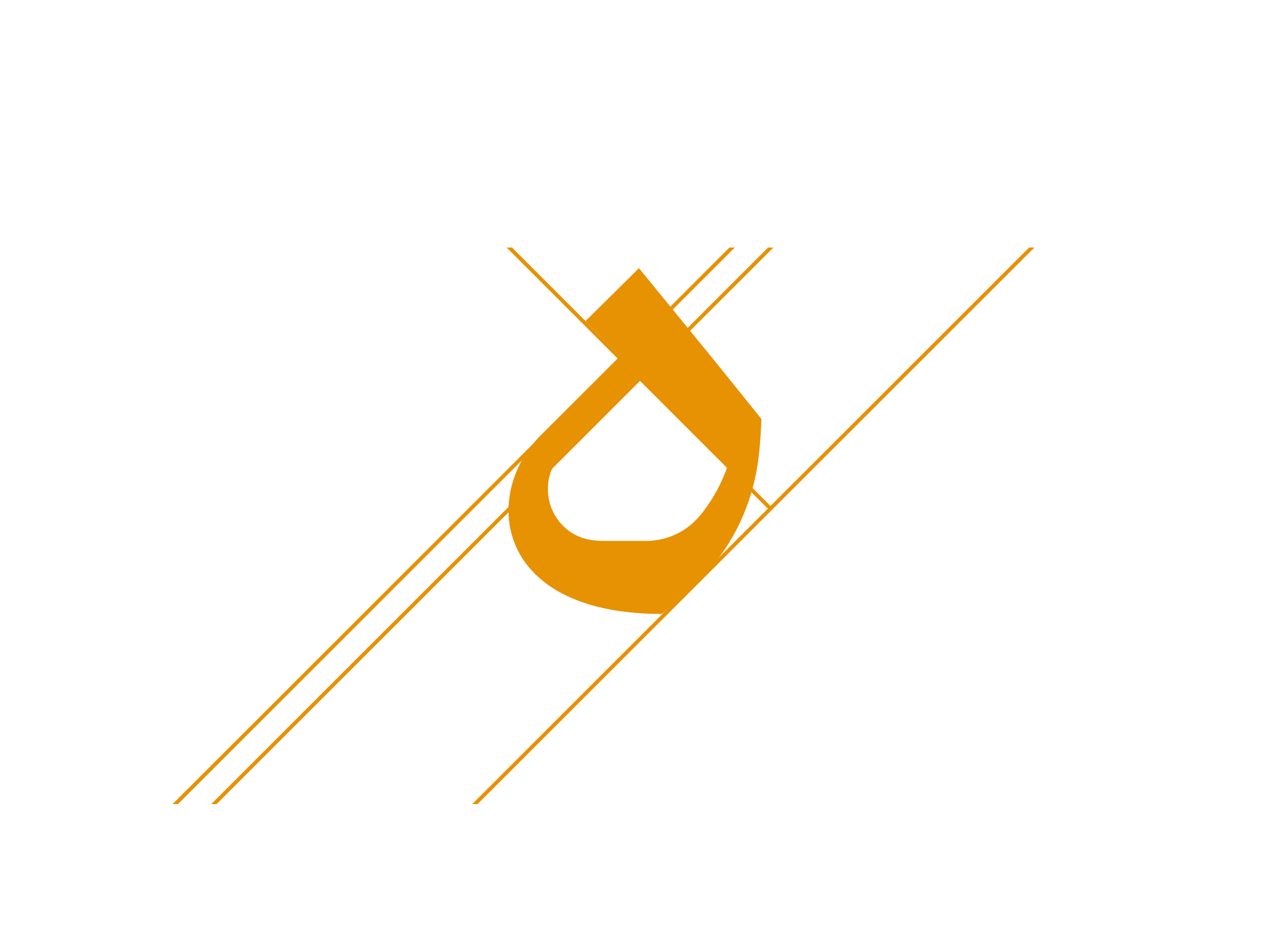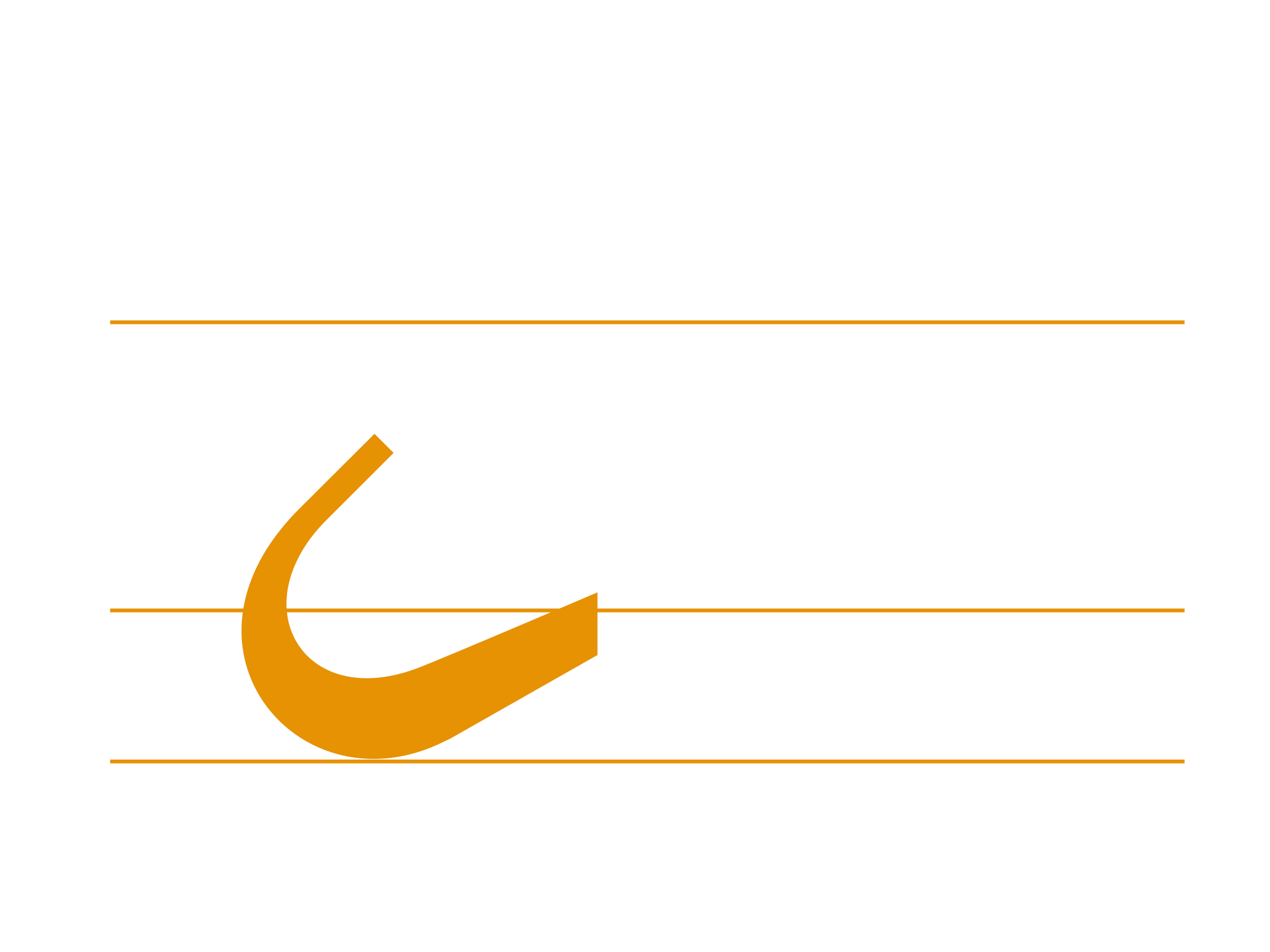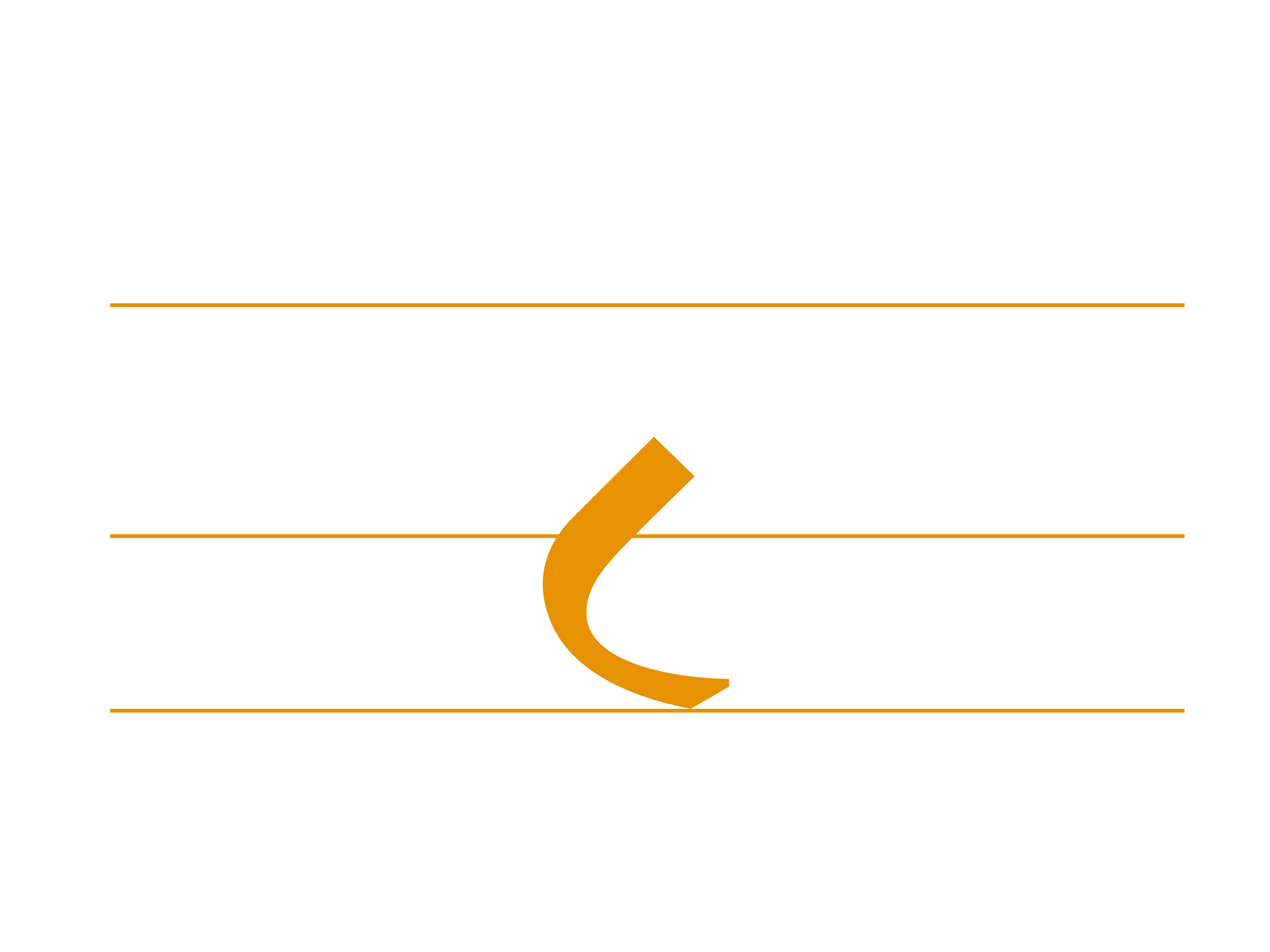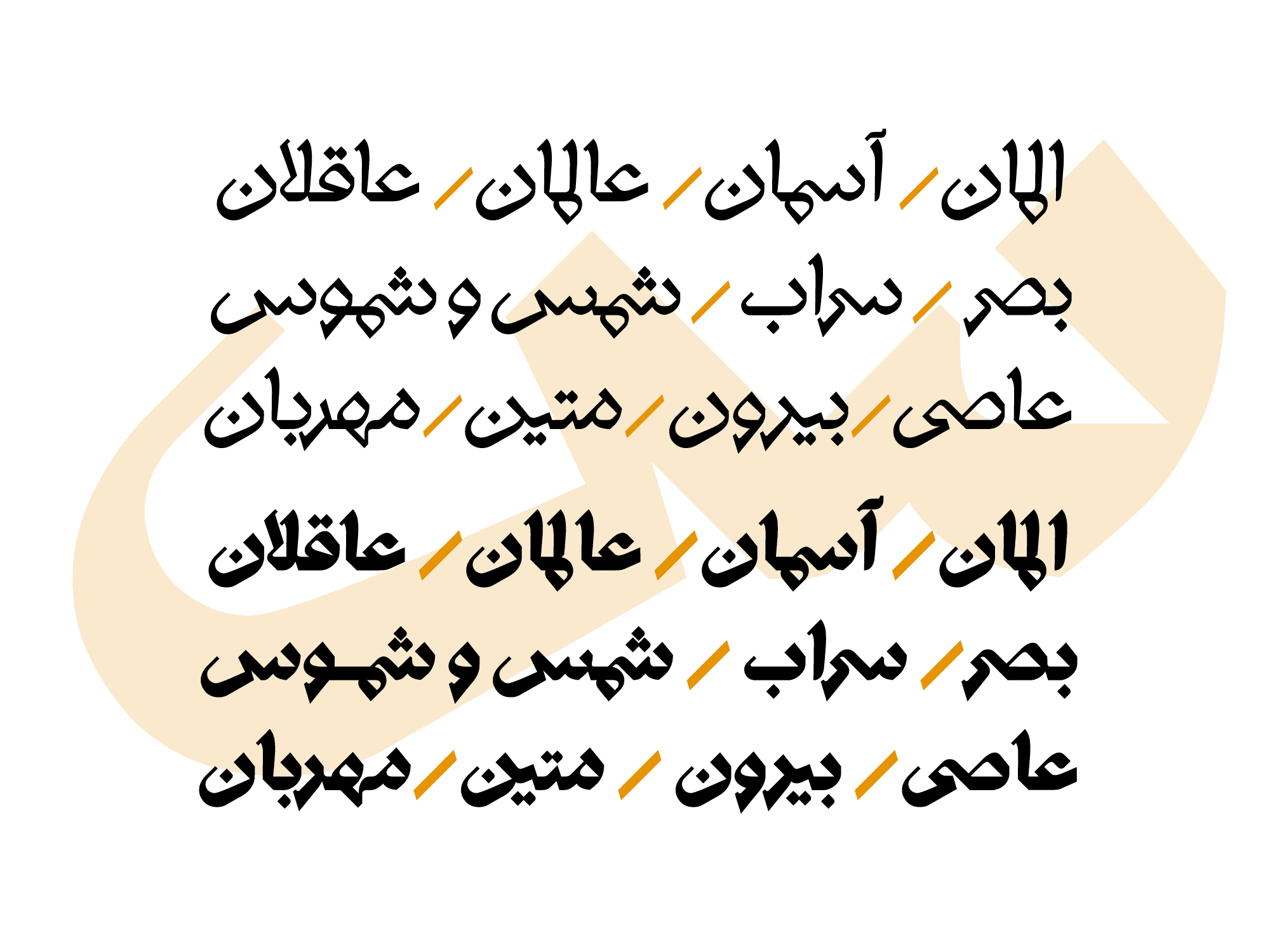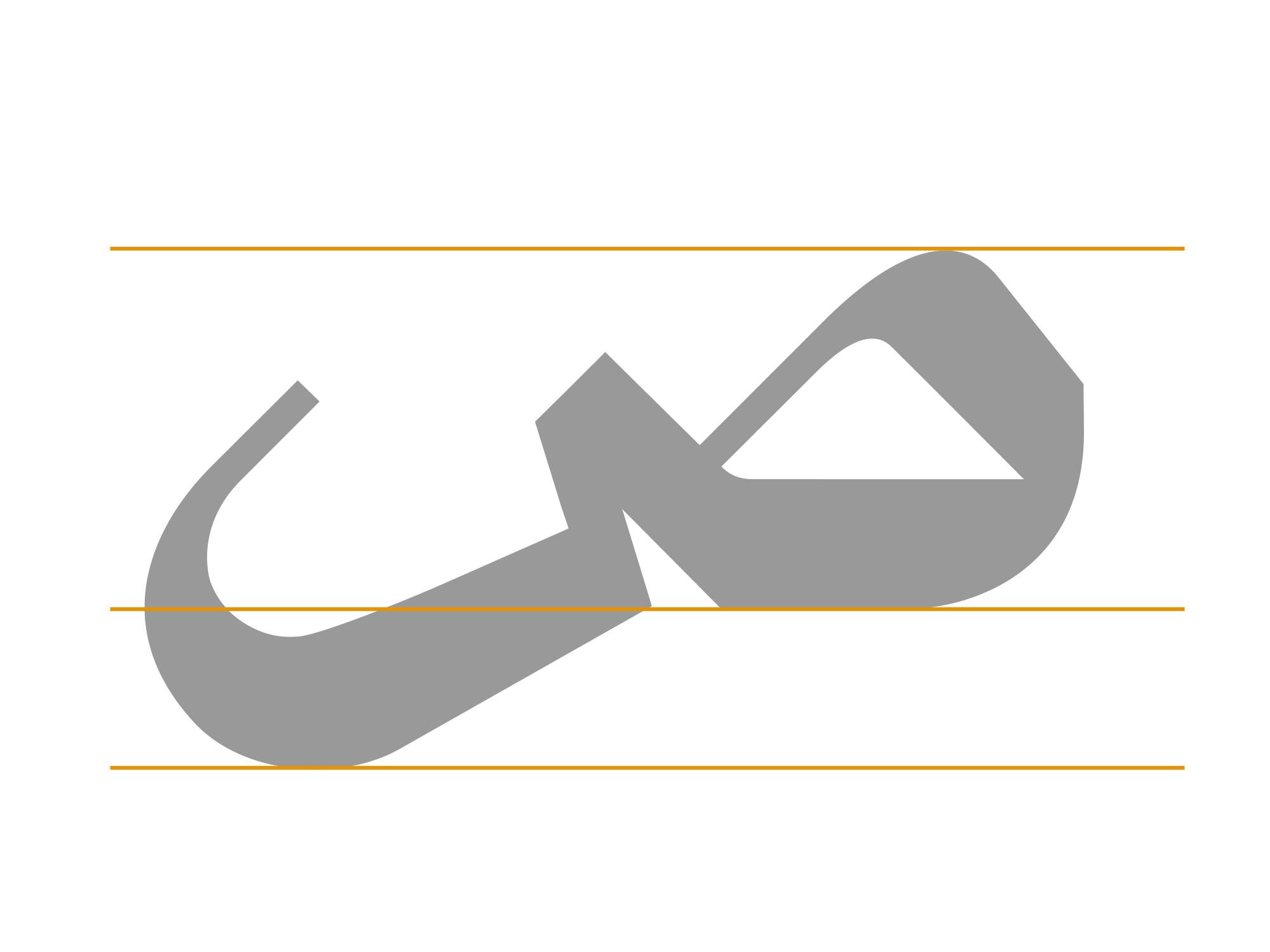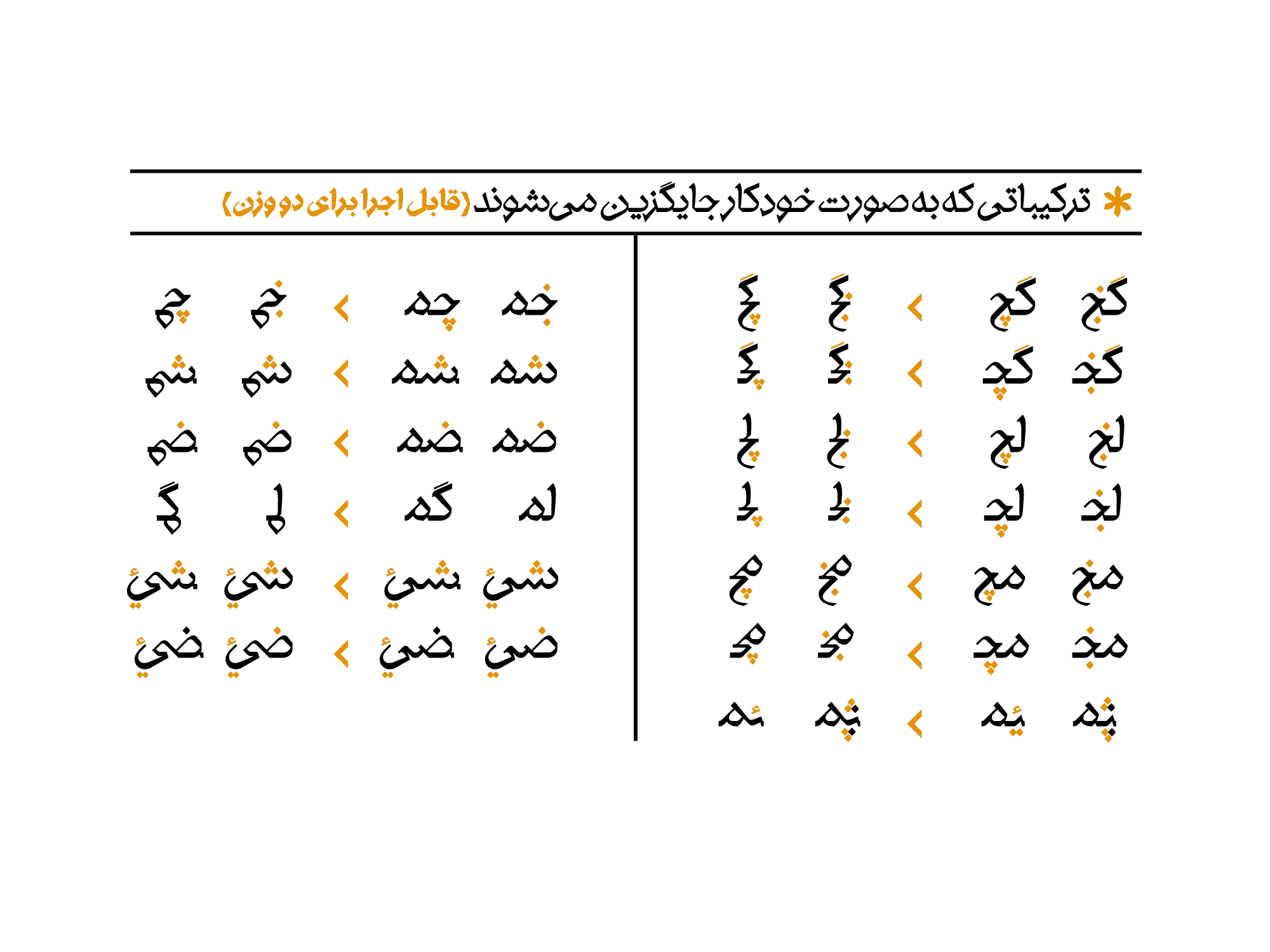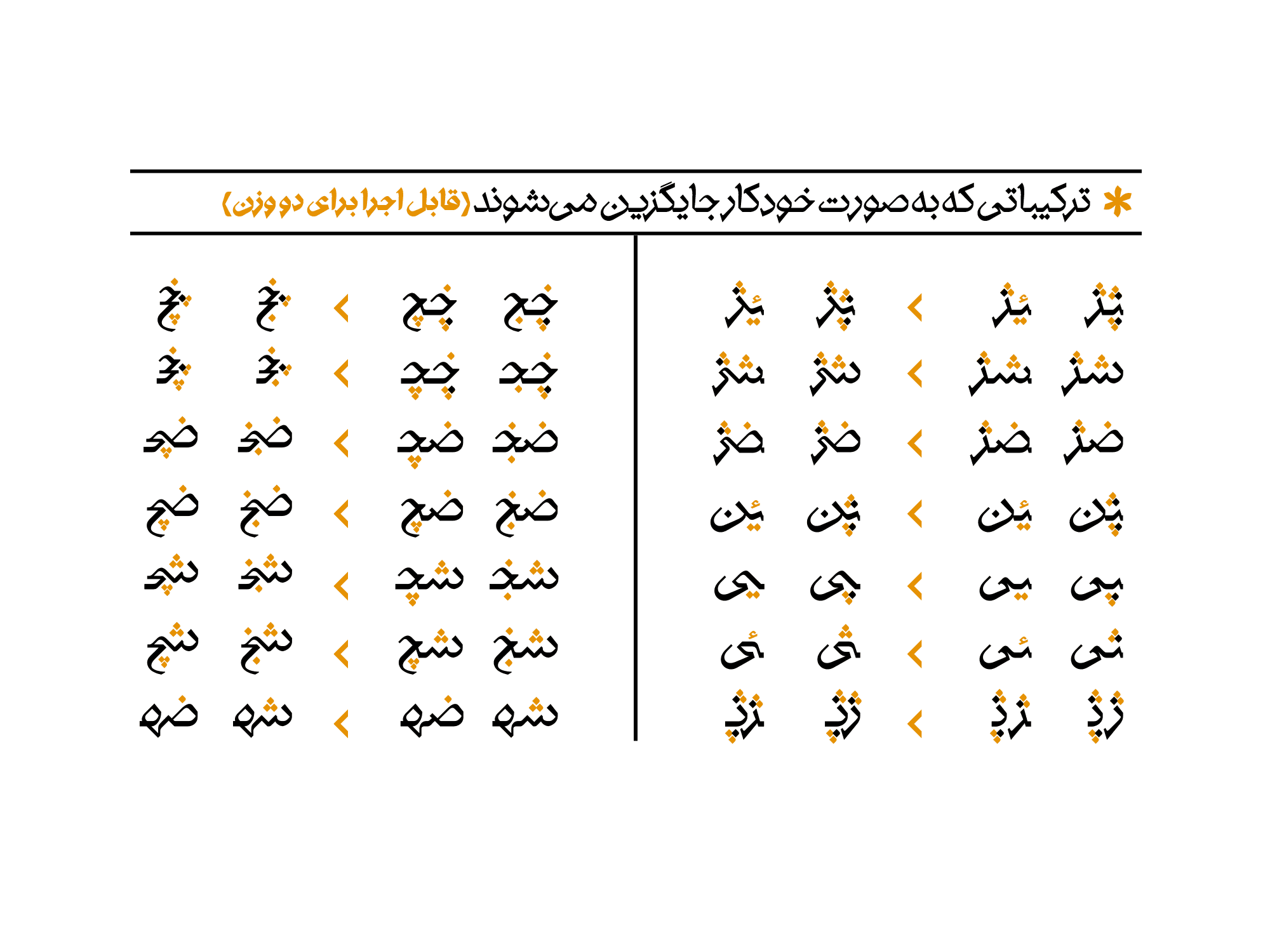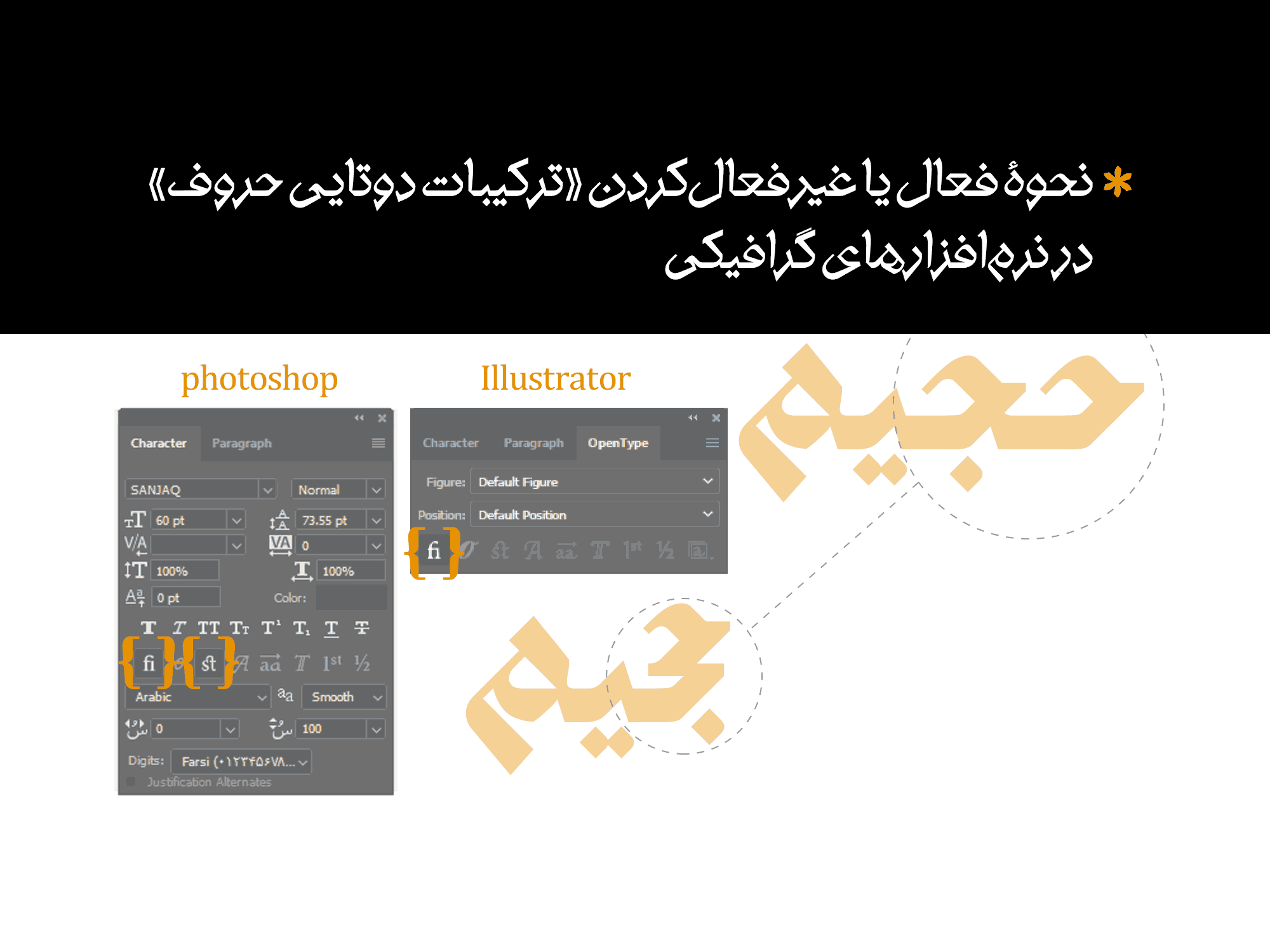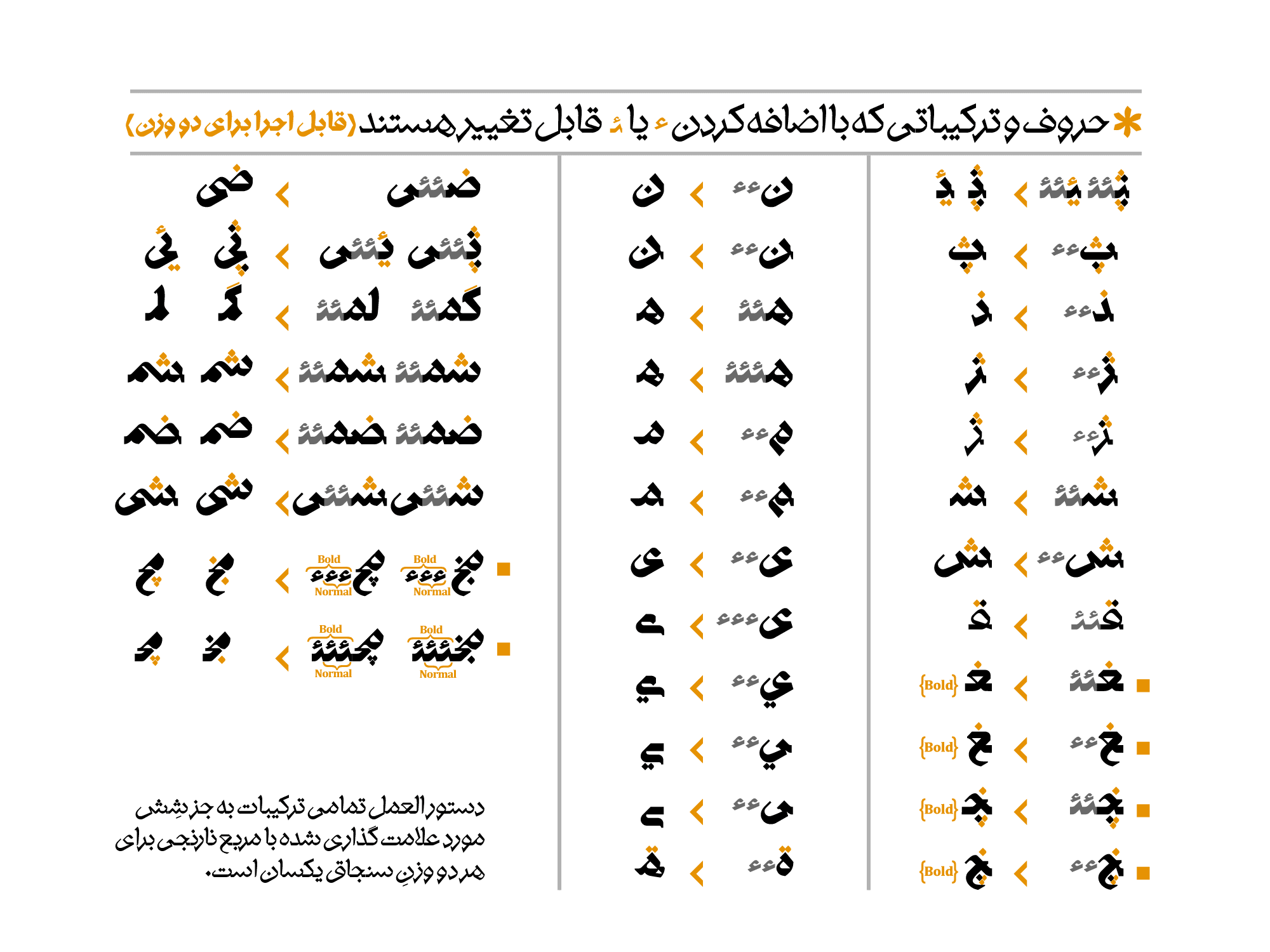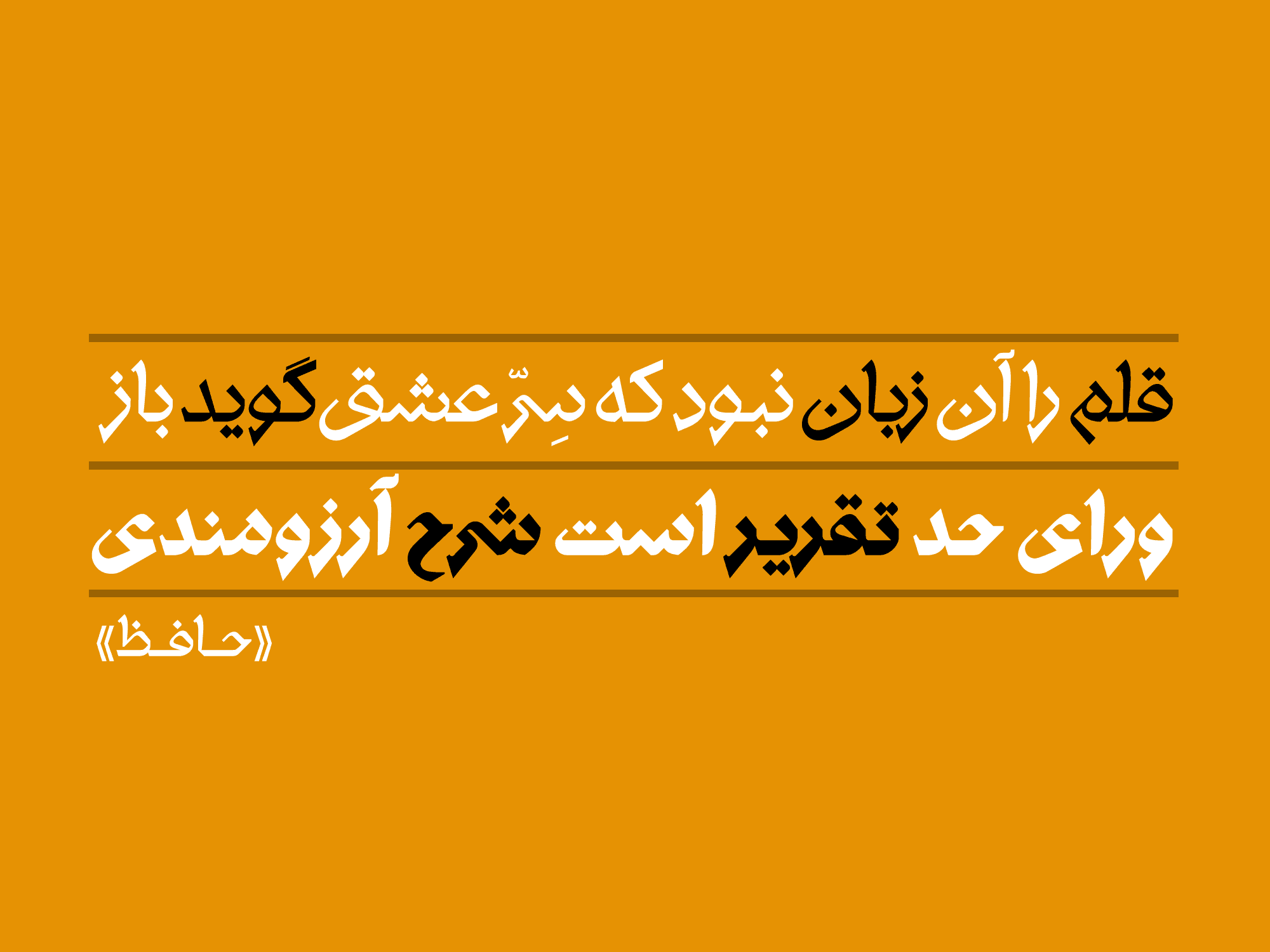
حروف در هر دو وزن سبک و سنگین دارای اسکلت، تناسبات ساختاری و محورهای رسامی مشترک هستند. (البته افزایش ضخامت در وزن سنگین قلم ناگزیر باعث تغییر نامحسوس شکل چشمیها شده است.) حروف در وزنِ سبُکِ سنجاق، اندامی استخوانی با فضاهای منفی باز دارند و اما در وزن سنگین آن، پر چگالی و فشرده هستند.
یکی دیگر از شاخصههای فرمی این قلم، لحاظ یک ضخامت ثابت برای نازکترین قسمت آناتومی حروف در دو وزن سبک و سنگین است: برای نمونه، ضخامت نازکترین بخش پایانۀ حروفِ س، ی، ن، ص در هر دو وزن سبک و سنگین ثابت است.
دیگر ویژگیهای فرمی این فونت به اختصار عبارتند از: چشمیهای درشت در وزن سبک، بهکارگیری حداقلی زواید و ضخامتهای تزئینی خطوط سنتی در پیکرۀ کاراکترها، طراحی لیگیچرهای متنوع (ترکیبات دوتایی حروف) و شکل دوم برای برخی از حروف که به صورت اتوماتیک و یا با اضافه کردن همزه پس از آن قابل دسترسی است.
خصایص ریختشناسانۀ مذکور، این فونت را مناسب برای طیف وسیعی از سفارشات و موضوعات کرده است. دو وزن قلم سنجاق برای انواع تایپوگرافی، طراحی عنوانبندی، لوگوتایپ و انواع متننویسی و برای طیف وسیعی از سفارشات (از فرهنگی تا تجاری) مناسب است.
فونت سنجاق، ظریف و طنّاز با شوری شاعرانه، متجددی پر جنب و جوش و پر نشاط، و در عین حال اصیل، جسور و محکم است.
اعداد و علائم نگارشی فونت سنجاق هماهنگ با شکل حروفِ آن طراحی شده است:
هر دو وزن فونت سنجاق با اعرابگذاری دقیق و طراحی گلیفهای مرتبط ، برای زبان عربی مناسبسازی شدهاند.
قلم سنجاق میتواند با تمامی فونتهای لاتین کلاسیک و پرکنتراستِ سریفدار (دارای زوائد تزئینی) همنشین شود؛ با اینحال، فونت انگلیسی "Cambria " با اندک تغییری در ضخامت، ارتفاع و فواصل (به قصد هماهنگی بیشتر ) برای «سنجاق» مناسبسازی شده است.